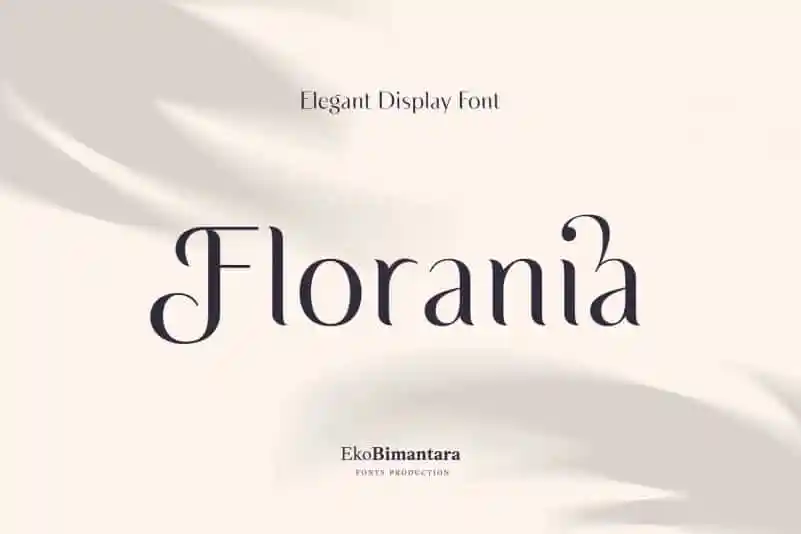
Florania Sans Serif Font – Download Grátis
A Florania Sans Serif é uma fonte sem serif que apresenta elegância e sofisticação. Ela destaca-se por sua aparência moderna e versátil, perfeitamente adequada para qualquer projeto visual atual ou futuro. Esta fonte oferece muitos alternativos e ligaturas a mais do que o padrão latino de linguagem, tornando-a especialmente versátil. Ideal tanto para aplicações de destaque como grandes tamanhos, também se adapta bem para projetos de design variados, desde logos e marcas até websites e logotipos. Com seu amplo leque de possibilidades, a Florania Sans Serif torna-se uma fonte perfeita tanto para ambientes digitais quanto impressos. Perfeito para desafios visuais diversos, é um recurso indispensável tanto para designers profissionais como iniciantes. Não deixe que qualquer projeto fique sem o brilho característico da Florania Sans Serif.